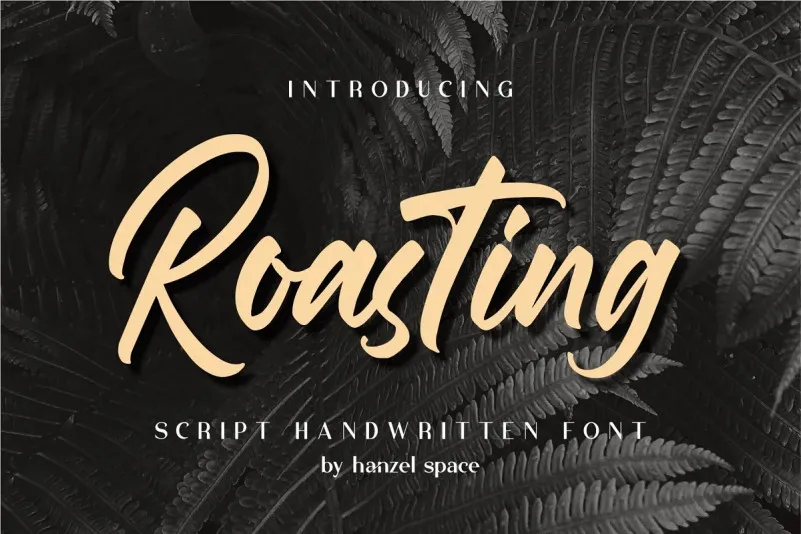
Esta fonte chamada Roasting foi criada pela Hanzel Studio e é uma fonte script com traços leves e fluidos que são perfeitamente adequados para criar identidades corporativas, cartões de convite de casamento, frases de marca, cartas ou até mesmo etiquetas e logos. Com um design leve e envolvente, a Roasting é perfeita para dar um toque elegante e personalizado a qualquer projeto gráfico. É uma ótima escolha para quem deseja adicionar uma pitada sofisticada e autêntica a seus materiais de marketing ou projetos digitais. Além disso, o seu design fácil de ler e flexível permite que você crie texturas únicas em variados formatos, tornando-a uma fonte versátil para designers gráficos experimentarem. Seja para criar um novo logo, personalizar a aparência de cartas ou adicionar uma toque especial aos teus materiais de marketing, a Roasting está aqui para dar o seu melhor.